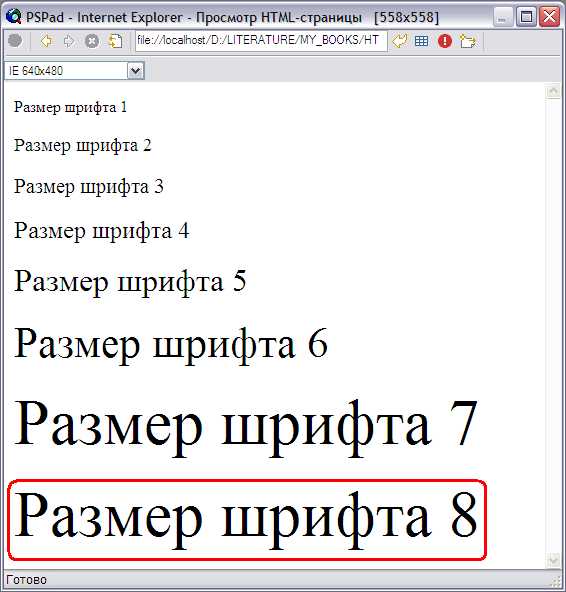
Шрифт является важной составляющей веб-дизайна, влияя на восприятие контента пользователем. Для корректного отображения текста на веб-странице необходимо правильно выбрать и задать шрифт через CSS. Это делается с помощью свойства font-family, которое позволяет указать семейство шрифтов, а также настроить альтернативные варианты на случай, если основной шрифт не доступен на устройстве пользователя.
Для того чтобы задать шрифт, нужно указать его имя в свойстве font-family. Стандартный подход заключается в использовании нескольких шрифтов, которые будут подставляться друг за другом. Например, сначала указывается основной шрифт, а затем через запятую – резервные. Это гарантирует, что в случае отсутствия выбранного шрифта в системе, текст отобразится в другом, схожем шрифте. Хорошей практикой является использование веб-шрифтов, доступных через сервисы, такие как Google Fonts, что позволяет обеспечить кросс-браузерную совместимость.
Чтобы подключить шрифт с помощью Google Fonts, достаточно вставить ссылку в head раздел страницы. Например, для шрифта Roboto это будет выглядеть так:
<link href="https://fonts.googleapis.com/css2?family=Roboto&display=swap" rel="stylesheet">
После этого можно применить шрифт к элементам на странице с помощью CSS:
body {
font-family: 'Roboto', sans-serif;
}
Кроме того, важно помнить о производительности. Использование большого количества шрифтов или нестандартных шрифтов может замедлить загрузку страницы, особенно если шрифт загружается с внешних ресурсов. Поэтому стоит выбирать только те шрифты, которые действительно необходимы для дизайна, и следить за их размером и количеством.
Как выбрать шрифт для веб-страницы в HTML
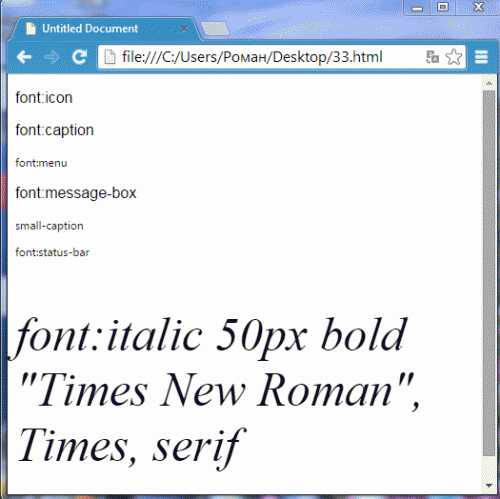
Первым шагом при выборе шрифта является понимание того, какой эффект вы хотите достичь. Для текстового контента, такого как статьи, блоги и новости, лучше всего подходят шрифты без засечек (sans-serif), так как они легче воспринимаются на экранах. Примеры таких шрифтов: Arial, Helvetica, Open Sans. Если же задача – создать более традиционный или официальный стиль, подойдут шрифты с засечками (serif), например, Times New Roman, Georgia.
Важно учитывать также доступность шрифтов на разных устройствах. Использование шрифтов, встроенных в системы (например, Arial или Times New Roman), гарантирует, что текст будет отображаться корректно, независимо от операционной системы. Однако для большего контроля над внешним видом можно подключать веб-шрифты через сервисы, такие как Google Fonts или Adobe Fonts.
При использовании веб-шрифтов важно помнить о производительности сайта. Чем больше шрифтов и стилей подключено, тем больше будет размер страницы, что может замедлить её загрузку. Для оптимизации стоит подключать только необходимые стили (например, только Regular и Bold, если другие не используются).
Кроме того, необходимо учитывать контраст шрифта и фона. Это поможет улучшить читаемость и восприятие текста. Для основного текста рекомендуется выбирать шрифт с хорошим контрастом на светлом фоне, а для заголовков можно использовать более выразительные шрифты с кеглем чуть больше, чтобы привлечь внимание.
Не забывайте о гибкости шрифта на разных устройствах. Использование относительных единиц измерения (например, em или rem) вместо фиксированных пикселей поможет шрифту масштабироваться в зависимости от размера экрана, что важно для адаптивного дизайна.